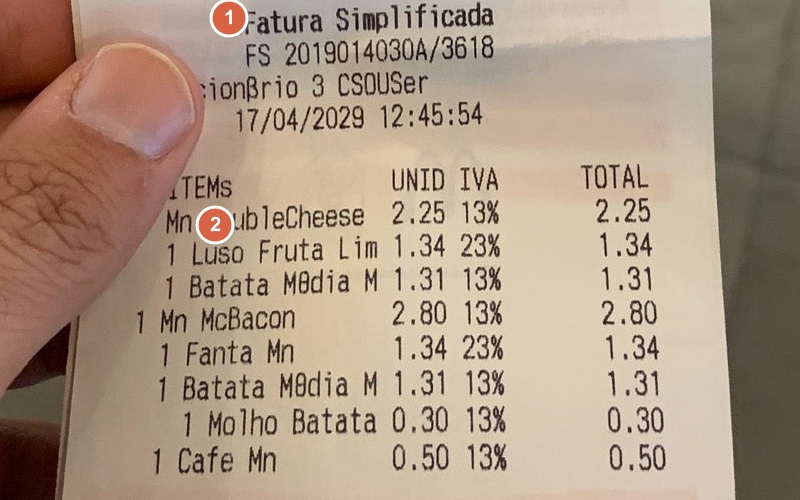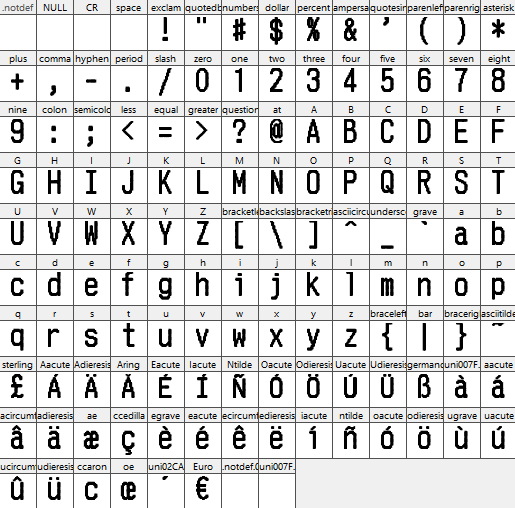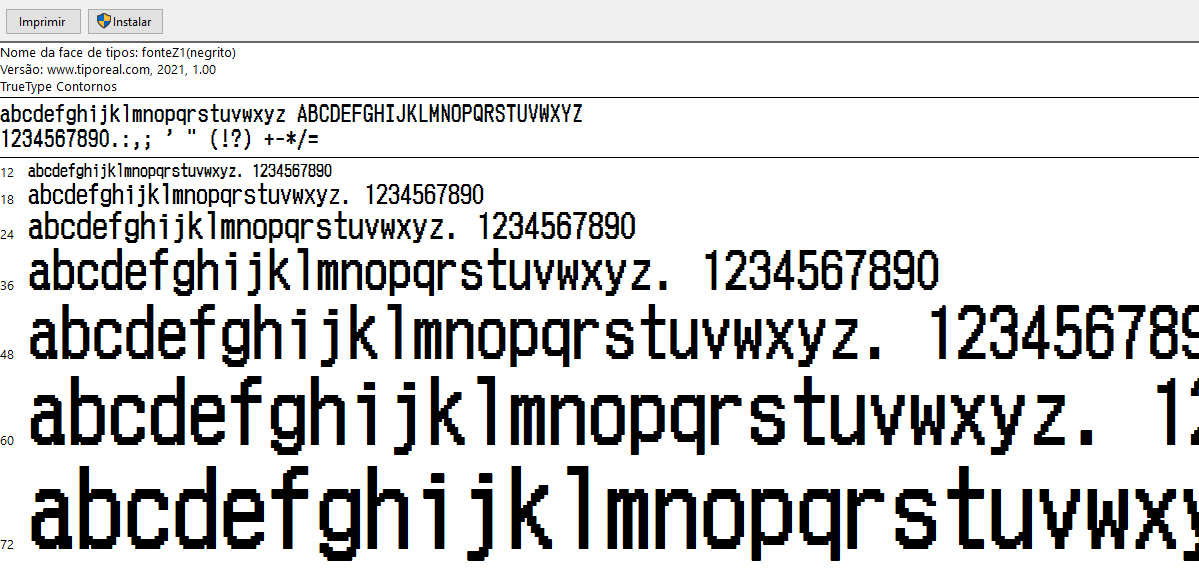
Amostra impressa da fonte para fatura simplificada de McDonald’s em Portugal (❶fonteZ1-negrito ❷fonteZ1)⤴
Todos os personagens⤴
O que parece quando aberto com o visualizador de fontes padrão do Windows⤴